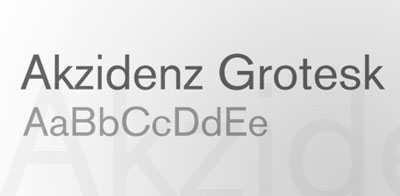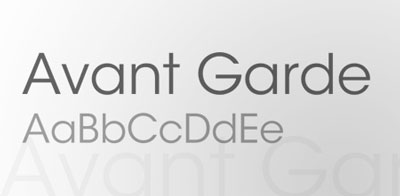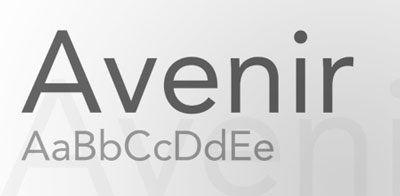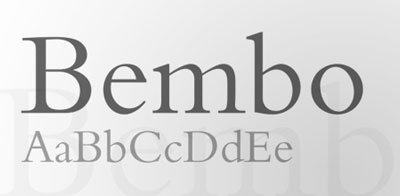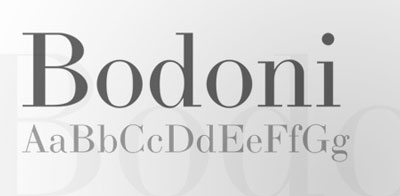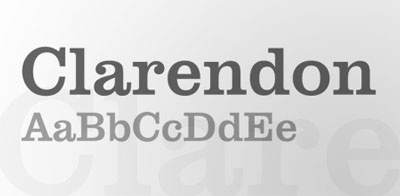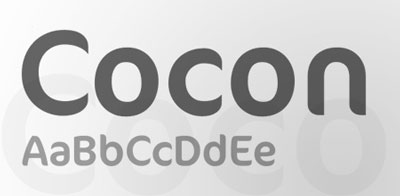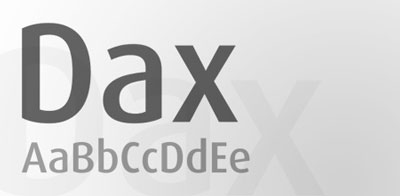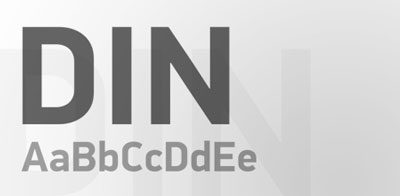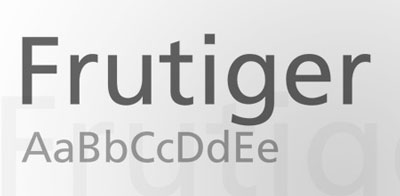
Las 25 tipografí­as más populares
Recientemente leí­ una publicación del diseñador Chris Spooner sobre las 25 tipografí­as más populares y utilizadas en el mundo del diseño y que seguirán teniendo vigencia y relevancia sin importar en que siglo estemos. El artí­culo me pareció muy interesante y decidí­ profundizar un poco más en dicha selección clasificándolas por clase y familia tipográfica.
Tipografí­as sin Serif
También llamadas de palo seco, estas tipografí­as se caracterizan por la ausencia de remates en los extremos. Aparecieron en Inglaterra durante la primera mitad del siglo XIX para su uso en impresos comerciales como carteles o etiquetas. Aquí­ encontramos las humaní­sticas, las geométricas y las grotescas.
• Sin Serif Humaní­sticas:
Están basadas en las proporciones de las inscripciones romanas mayúsculas y en la escritura manual de caja baja de los humanistas renacentistas. Los grosores de los trazos no son uniformes y presentan cierta modulación.
Gill Sans
Diseñada por Eric gill en 1926, Gill Sans es una de las fuentes más utilizadas en materia de Diseño Gráfico.  Se trata de una tipografí­a muy legible, con una alta dosis de originalidad y una personalidad muy moderna.
Optima
Optima es una tipografí­a de origen alemán diseñada por Hermann Zapf en 1958. Elegante y legible, es una mezcla entre la objetividad de los tipos de palo seco y el estilo y la claridad de las letras con serif.
Frutiger
Creada por Adrian Frutiger en 1976 para un sistema de señalización para el aeropuerto de Charles de Gaulle. La diseña para cumplir los requisistos de legibilidad, facil y rápido reconocimiento a grandes distancias que un  sistema así­ requiere. Su enorme calidad hizo que trascendiera esta función y hoy sea una de las tipografí­as más utilizadas en estudios de diseño con un uso casi universal.
Meta –  (Neohumaní­stica)
FF Meta es una tipografí­a diseñada por Erik Spiekermann en 1986.
Dax
La fuente Dax, ahora utilizada por la marca UPS, fue originalmente creada por Hans Reichel.
Myriad
Myriad fue creada especialmente para Adobe por Rober Slimback y Carol Twomblyen 1992. Posee legibilidad, calidez y comodidad propias de los tipos sin serifs humaní­sticas. Es la que aparece por defecto en las aplicaciones de Adobe.
• Sin Serif Grotescas:
Llamadas «Gothic en Estados Unidos, fueron las primeras tipografí­as sin serif que datan del siglo XIX. Caracterí­stica: existe un ligero o muy poco marcado contraste entre palos.
Akzidenz Grotesk (Neogrotesca)
Akzidenz Grotesk fue diseñada en 1896 por Günter Lange para la fundición Berthold en Berlí­n. Esta tipografí­a es la precursora de la Helvética.
News Gothic
News Gothic fue diseñada por Morris Fuller Benton en 1908, y tiene la particularidad de ser la tipografí­a utilizada para el comienzo de los créditos en Guerra de las Galaxias.
Helvetica (Neogrotesca)
Una de las tipografí­as más populares del mundo. Fue creada por el diseñador suizo Max Miedinger bajo el encargo de Edouard Hoffmann, de la Fundición Hass en 1957. La Helvetica es una tipografí­a con una alta legibilidad y eficacia en todo tipo de situaciones y fue gracias a ella, por la que Max Miedinger pasó a la historia de la tipografí­a.
Univers (Neogrotesca)
Univers es otra clásica de Adrian Frutiger, diseñada en 1957. Tiene el estilo tí­pico suizo y es frecuentemente confundida con la Helvética o la Akzidenz Grotesk.Univers
Rotis (Neogrotesca)
Rotis fue diseñada para una gran y excepcional legibilidad. Fue creada por Olt Aicher en 1988.
• Sin Serif Geométricas:
Nacen en 1929, consecuencia de las vanguardias y la Bauhaus. Construidas a partir de lí­neas rectas y figuras geométricas como el cí­rculo y el cuadrado, son minimalistas, sin modulación ni variaciones de los grosores de los palos.
Futura
Futura es otra tipografí­a utilizada de forma masiva y  puede apreciarse en incontables logos. Fue originalmente creada por Paul Renner en los años 1920.
Avant Garde
Tipografí­a basada en el logo que Herb Lubalin diseñó para la revista Avant Garde Magazine en 1967, y que serí­a rediseñada en 1970 por el genial tipógrafo junto con Tom Carnase, añadiéndole los caracteres de caja baja. Se trata de una tipografí­a geométrica, formada a base de cí­rculos y lí­neas rectas y que fue inspirada en la Futura de Paul Renner y en el movimiento alemán de la Bauhaus de los años 20.
VAG Rounded
Esta tipografí­a aparece en numerosos logos de la Web 2.0, pero fue originalmente diseñada en 1979 para la identidad corporativa de Volkswagen.
Avenir
Esta tipografí­a también fue diseñada por Adrian Frutiger, en 1988.
DIN
FF Din no entrarí­a exactamente en la categorí­a de las geométricas, sino que podrí­a tener un lugar dentro de las sin serif cuadradas y fue creada en 1995 por Albert-Jan Pool.
Clarendon
Clarendon fue creada Robert Besley en 1845.
Rockwell
Rockwell es probablemente la más tí­pica de las tipografí­as slab-serif. Fue diseñada por Monotype en 1934 y ahora es utilizada en todo tipo de diseños que requieren gran impacto visual.